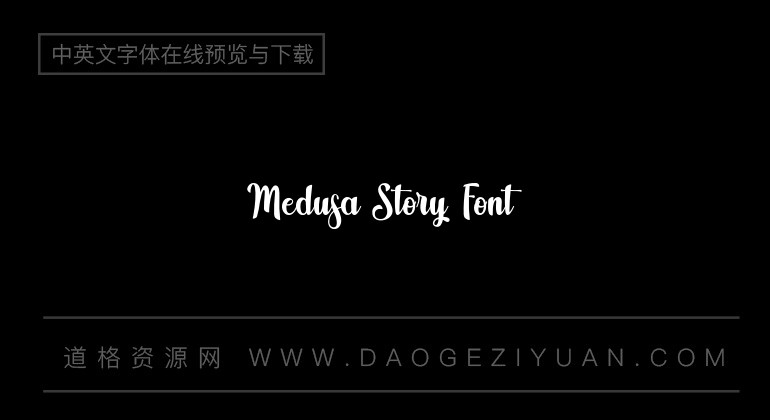
Medusa Story Font是一款华丽的手写字体,具有古老的希腊艺术风格。它取材于希腊神话中的美杜莎,字体设计灵感来自于她的丰富多彩的头发以及神秘的形象。 这个字体具有许多华丽的特点,包括流畅的笔画和精美的细节。每个字母都被设计成独特的形状,带有独特的线条和流动的曲线。这使得Medusa Story Font非常适合用于标题、标志、海报和其他需要引人注目的设计项目。 此外,Medusa Story Font还包括大量的特殊字符和符号,可以用于增强设计的创意性和美学价值。总之,这个字体是一款非常吸引人的选择,能够为你的设计项目带来无限的创意和独特性。内容介绍
Medusa Story Font是一款非常不错的手写艺术字体,具有很好的视觉感,适合于文化类的宣传设计、商业类品牌的广告和产品包装设计以及个性化文字排版等较多场景。